Font Việt Hóa Là Gì? Phân Biệt Font Việt Hóa Và Font Quốc Tế
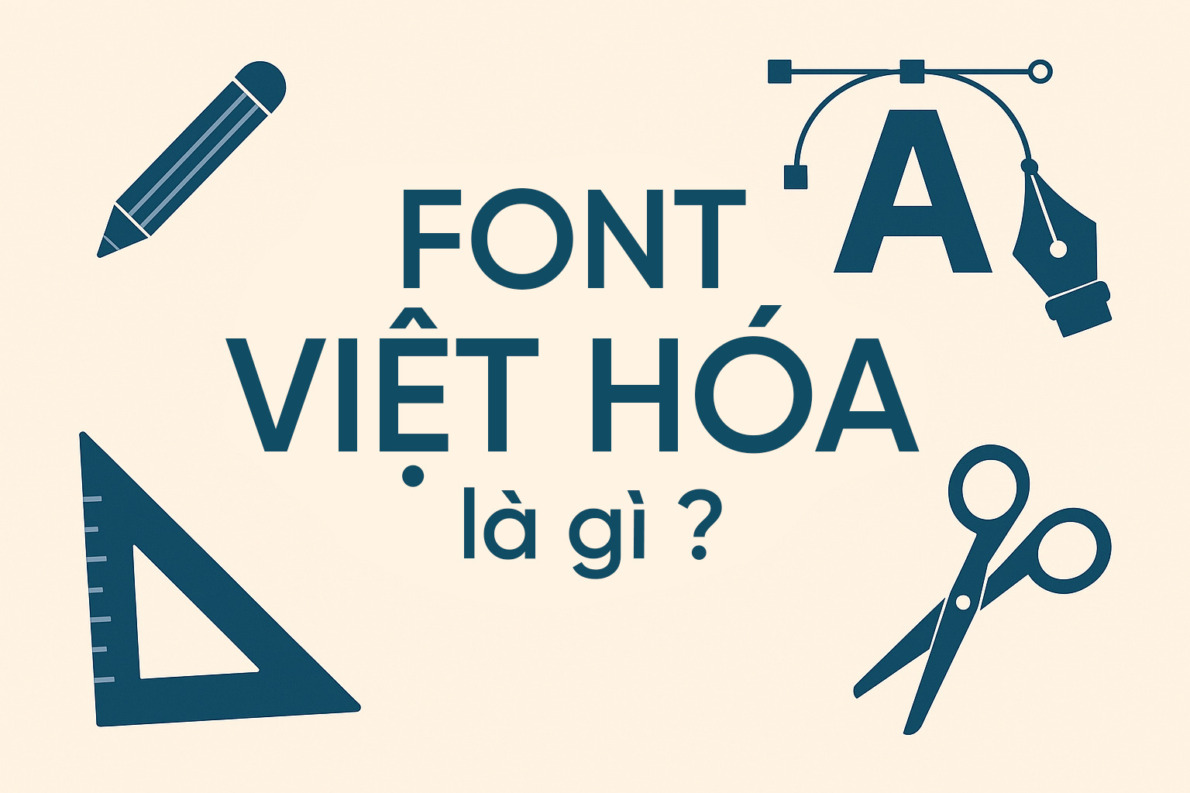
Trong thiết kế và trình bày nội dung tiếng Việt, font chữ đóng vai trò cực kỳ quan trọng. Việc chọn đúng không chỉ giúp đảm bảo nội dung hiển thị chính xác mà còn mang lại tính thẩm mỹ chuyên nghiệp. Vậy font Việt hóa là gì? Làm sao để phân biệt với các font quốc tế chưa hỗ trợ tiếng Việt? Bài viết dưới đây sẽ giúp bạn hiểu rõ tất cả.
Font Việt Hóa Là Gì?
Là các bộ font chữ gốc nước ngoài (thường là tiếng Anh hoặc các font Latin) được tinh chỉnh lại để hỗ trợ đầy đủ ký tự tiếng Việt như: ă, â, ê, ô, ơ, ư, đ,…
Việc Việt hóa không chỉ đơn giản là thêm dấu, mà còn đòi hỏi việc canh chỉnh lại khoảng cách, độ cao, nét chữ sao cho hài hòa với thiết kế ban đầu. Nhờ đó, khi sử dụng trong thiết kế hoặc in ấn, nội dung sẽ không bị lỗi hiển thị hoặc sai dấu.
Lợi Ích Khi Sử Dụng
Hiển thị đúng tiếng Việt, không lỗi dấu
Dễ dàng sử dụng trong các phần mềm thiết kế như Photoshop, AI, Canva
Đảm bảo sự nhất quán trong in ấn, trình bày
Mang lại trải nghiệm đọc thân thiện và chuyên nghiệp hơn
So Sánh Font Đã Việt Với Font Quốc Tế
| Tiêu chí | Font đã Việt Hóa | Font Quốc Tế Gốc |
|---|---|---|
| Hỗ trợ tiếng Việt | ✔️ Có đầy đủ dấu và ký tự | ❌ Không hỗ trợ dấu |
| Tương thích thiết kế | Cao, đẹp | Có thể bị lệch dấu |
| Ứng dụng | Phù hợp với nội dung tiếng Việt | Chủ yếu dùng cho tiếng Anh |
Ví dụ: SVN Gotham (Việt hóa từ font Gotham), iCiel Pacifico Việt hóa, UTM Avo Việt hóa là những font tiêu biểu.
Cách Kiểm Tra Font Đã Việt Hóa Hay Chưa
Gõ thử các từ có dấu như: cảm ơn, đừng, ước mơ, trường lớp…
Nếu phong hiển thị đầy đủ, dấu đúng vị trí, đồng đều → Phong đã được Việt hóa.
Nếu dấu bị lệch, mất hoặc hiển thị sai → Là font chưa Việt hóa.
Gợi Ý Một Số Font Nên Dùng
SVN-Gotham – hiện đại, dễ đọc
iCiel Cadena Script – viết tay nghệ thuật
UTM Avo – sans-serif tối giản
iCiel Pacifico Việt hóa – phong cách vintage, phá cách
Kết Luận
Việc phân biệt với các phong quốc tế chưa Việt hóa sẽ giúp bạn tránh lỗi hiển thị không mong muốn, đặc biệt trong các ấn phẩm in ấn, truyền thông và thiết kế kỹ thuật số.